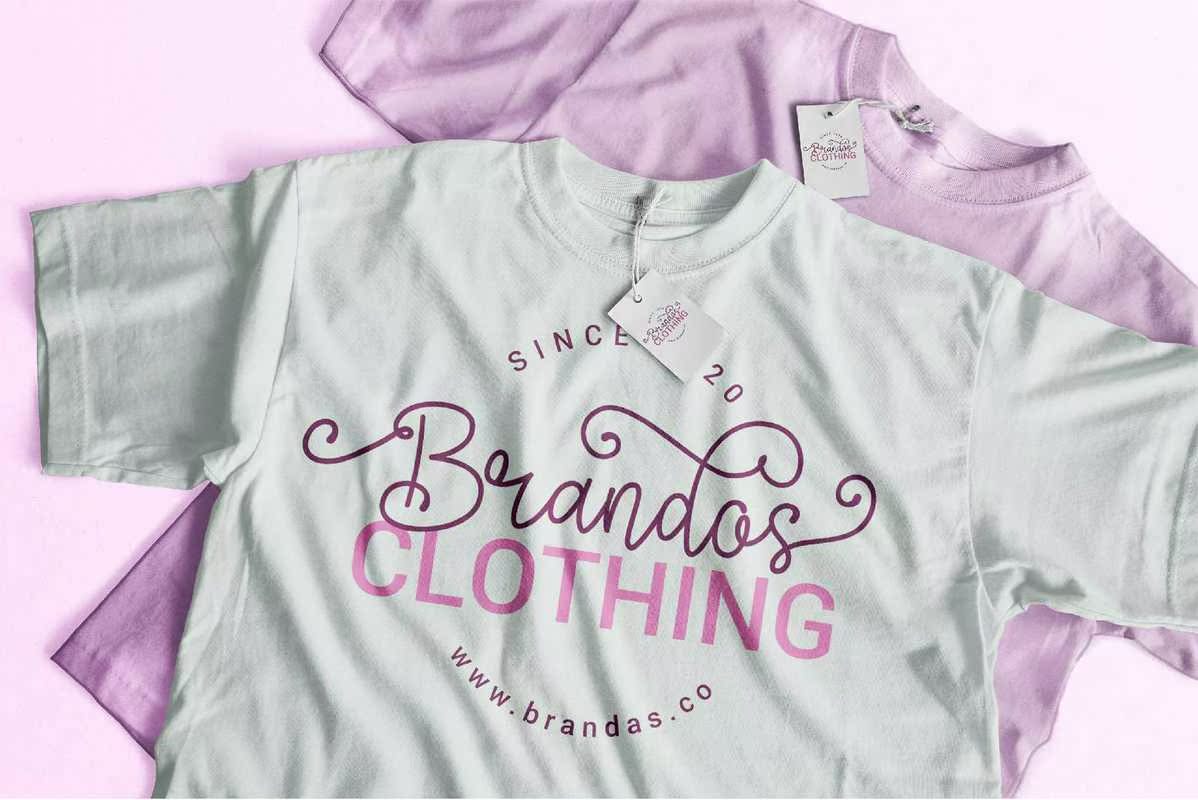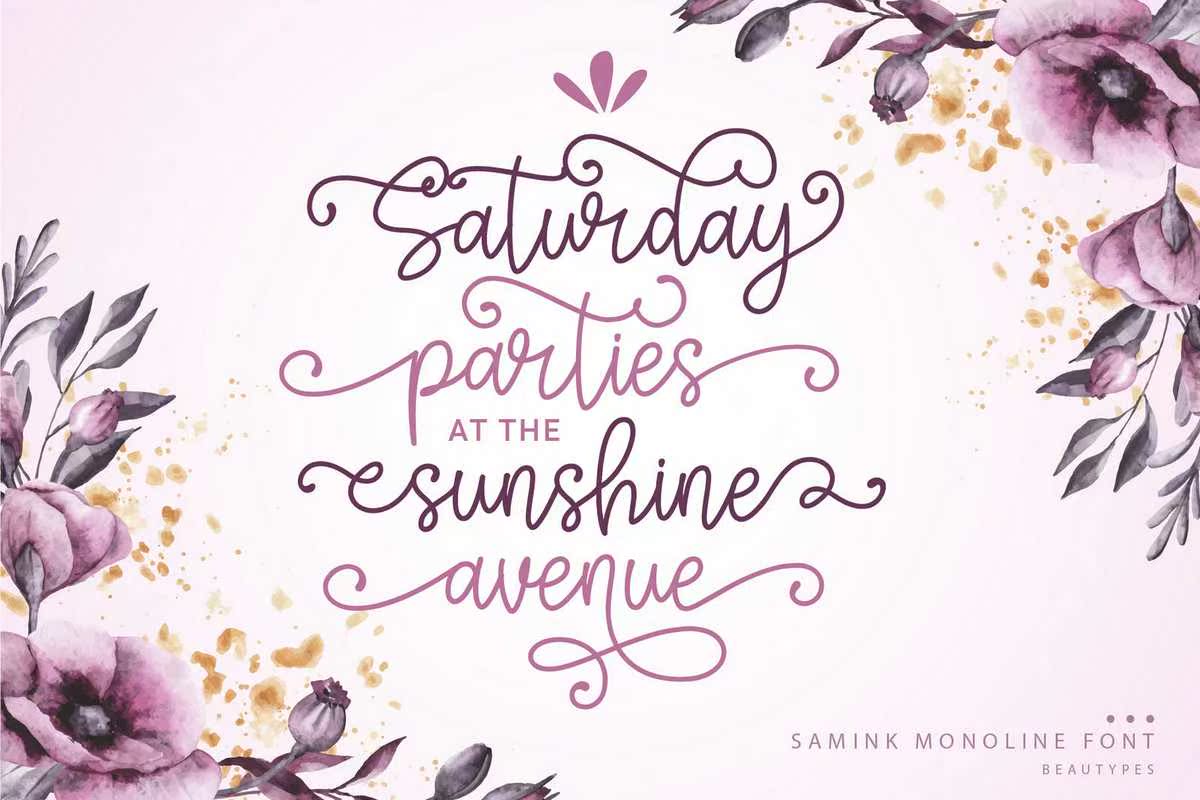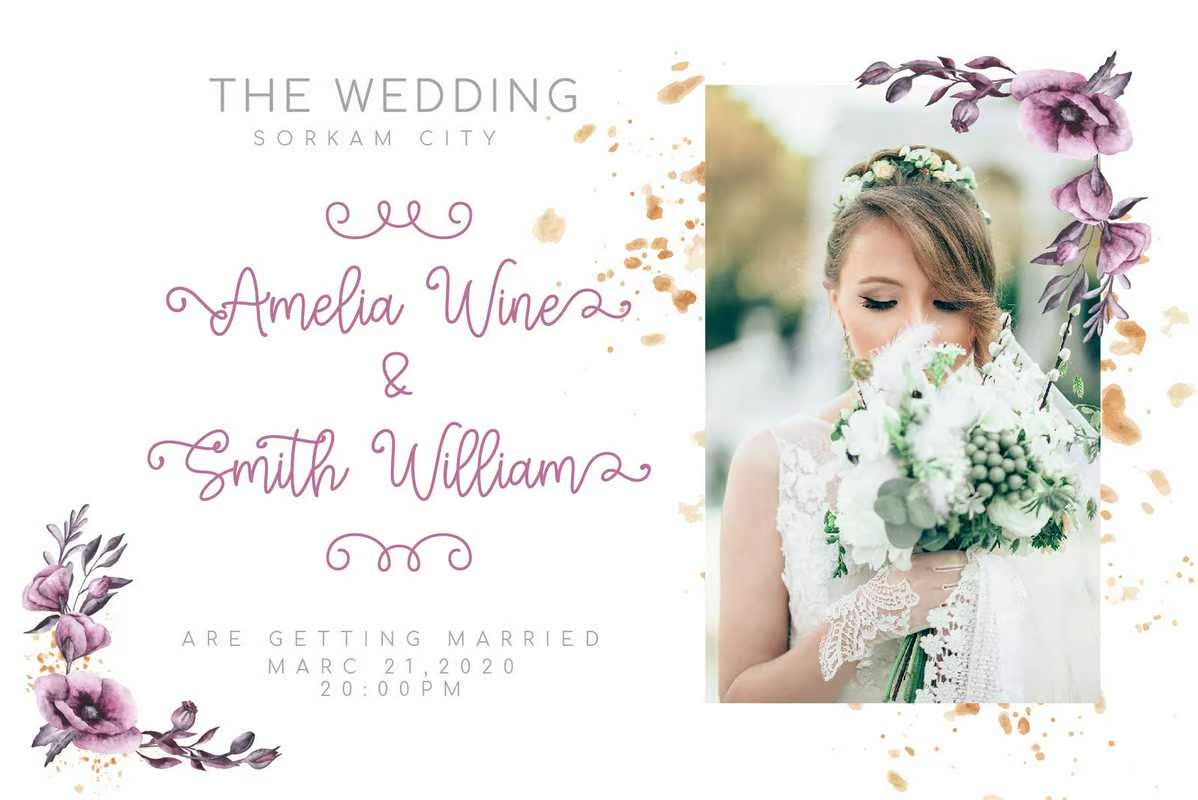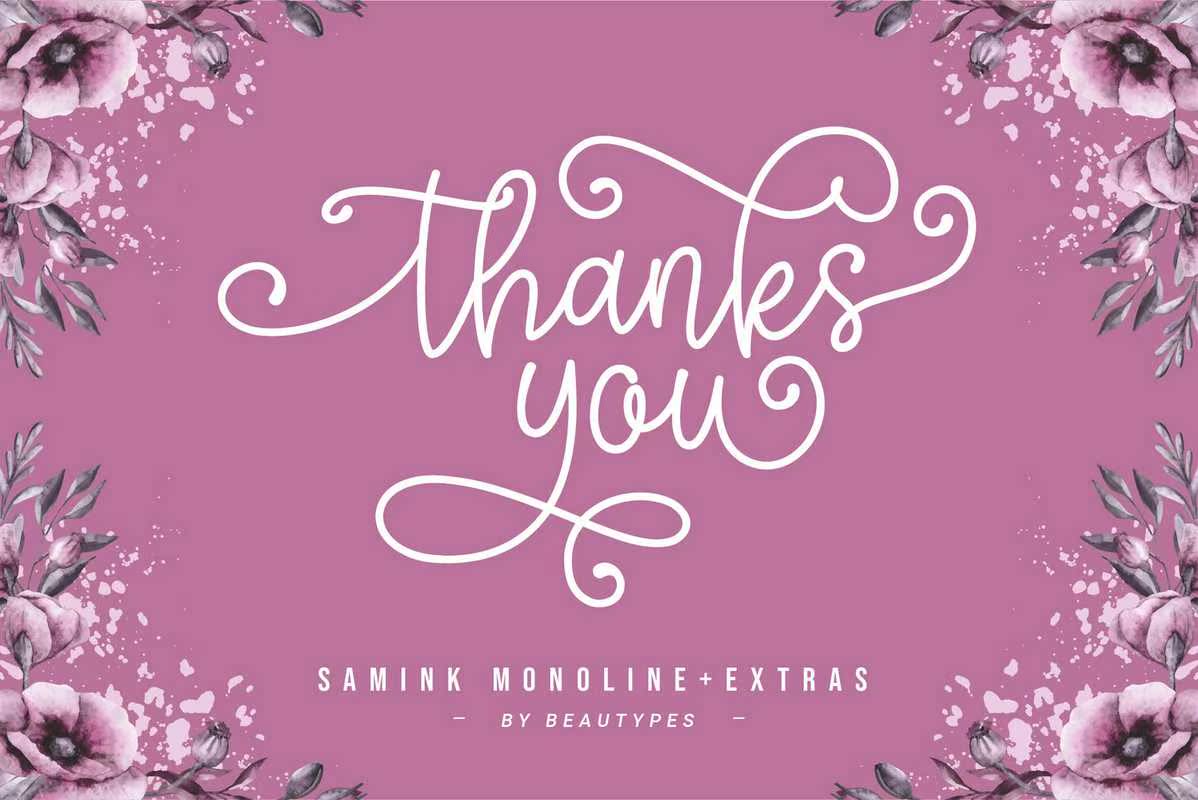
为任何需要的印刷字体设计相同的单线字体,使其能够完美组合,并且能够快速、方便地创建令人震惊的手写字体。;这是给你带来敏感和浪漫的最佳方式。它的特点是装饰性角色和舞蹈基线!。为任何需要的印刷字体设计相同的单线字体,使其能够完美组合,并且能够快速、方便地创建令人震惊的手写字体。;这是给你带来敏感和浪漫的最佳方式。它的特点是装饰性角色和舞蹈基线!。